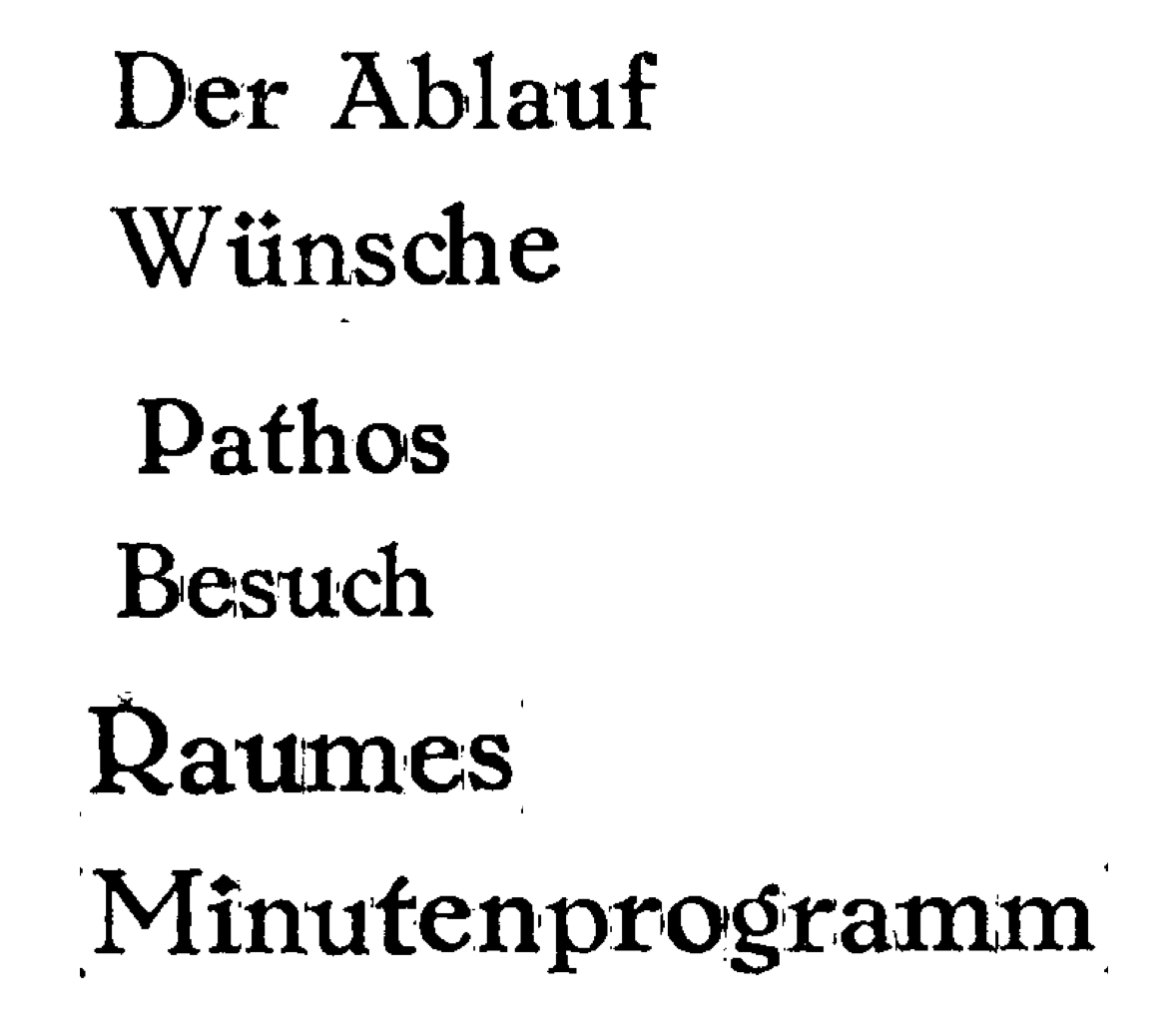
Schriftart gesucht - Kriegszeit
von vorliegender Schrift konnte ich bislang nicht den Schrifttyp ermitteln, obwohl ich schon starke Ähnlichkeiten gefunden habe.
Es muß amtlich oder halbamtlich (z. B. bei der SS) verwendet worden sein und stammt - wie gesagt - aus Kriegszeiten, etwa 1942.
Ich hoffe, jemand kann mir den Schrifttyp nennen.
Die genannte Schrift: Berthold - Alt-Mediäval
Es gibt die "New Mediäval", a revival of Max Hertwig’s Alt-Mediäval (Berthold, 1914). Started in 2015–2017 at ECAL, under the guidance of François Rappo and initially named Alt Mediaeval V.2. Available on request. To be released with Kyiv Type Foundry as New Mediäval.